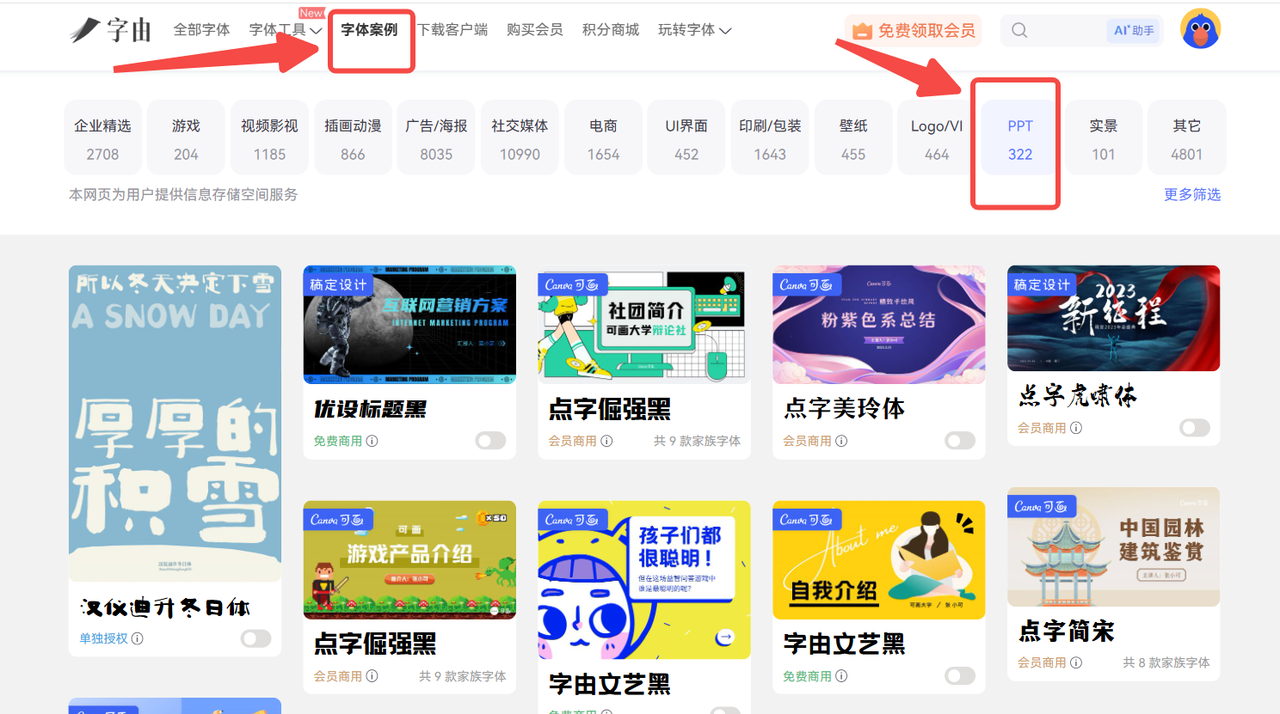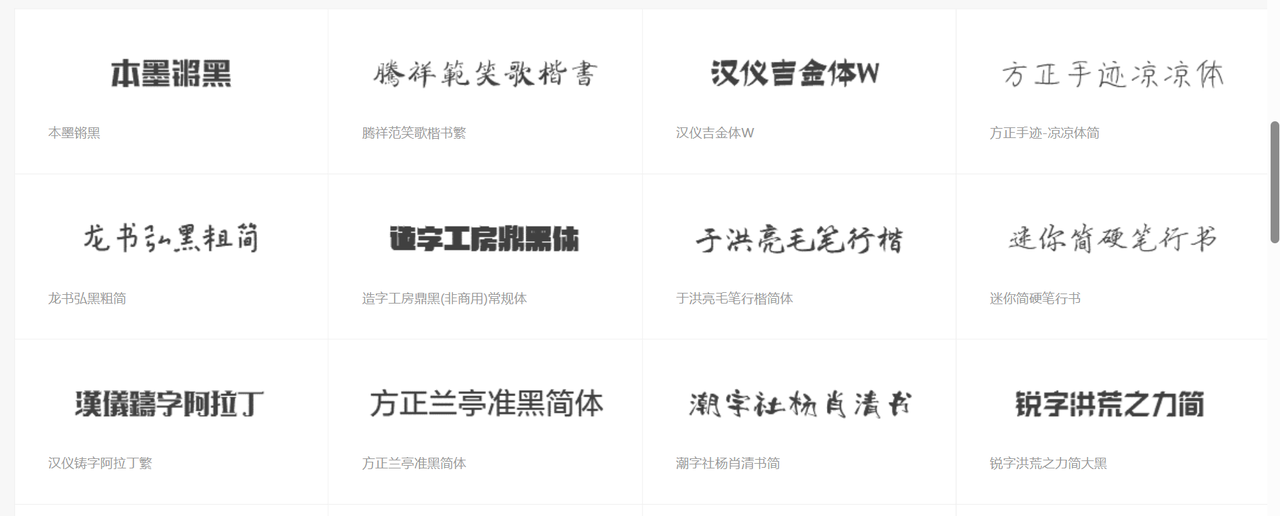
理想的PPT字体是什么样?字体使用避坑指南
理想的 PPT 字体是什么样?抛开宋体和微软雅黑,来寻找可以提升质感的 PPT 字体吧!一般来说,我们可以把 PPT 的文字内容划分为两部分,即标题和正文。像标题,既要凸显主题又要保证不突兀,我们就可以选择黑体或者楷体。而正文由于字数过多,保证排版的同时也不能丢掉可读性,我们就可以看一下无衬线体,比如阿里巴巴普惠黑。而好用的字体也离不开方便使用的字体网站,接下来,本文就将结合几个好用的字体网站来为你推荐更理想的 PPT 字体,一起往下看吧!
1、多款正版 PPT 字体,前往【字由】直接使用
字由是一个素材丰富,风格多样的字体网站,如果你在设计 PPT 时,对于字体的使用没有任何思路的话,那么可以先来【字由】中寻找灵感。字由站内汇集了上万款精品正版字体素材,不仅包含常用的中文字体,还有英文字体,日文,韩文和泰文等,即便是需要做小众语言的 PPT 设计,也能够在字由中找到喜欢的字体。不仅字体素材丰富,字由站内的字体风格也十分多样,不管是需要简约风还是古典风,亦或是卡通风,手写风,科技感,字由站内均有对应的字体素材可供挑选,满足你设计 PPT 时的多种用字需求。
如果面对上万款字体素材,不知该如何下手的话,不要着急,字由还有另一个好用的功能可以帮助你。打开字由官网后,我们可以访问导航栏中的【字体案例】区域,这里按设计场景分类提供了或许更合适你使用的字体素材。我们将设计场景选为 “PPT”,之后在下方就能看到官方推荐的在 PPT 设计中更常用,更好用的字体素材。
以答辩 PPT 为例,我们在规划 PPT 的文字内容时,标题部分传递主题信息,肯定要突出显示,我们就可以选择比较醒目的字体,例如优设标题黑,字由文艺黑,点字简宋,点字倔强黑等,而正文部分由于传达的信息比较多,我们在保证字体美观度的同时也要确保可读性,正文就可以选用非衬线字体,比如 Milky Han Te 家族字体。以上字体都可以在字由中立即使用,并且均拥有正版授权,无需担心侵权风险。
2、优品 PPT:高质量 PPT 网站,精美 PPT 字体推荐
优品 PPT 是一个专业设计 PPT 的网站,它站内提供了周全的 PPT 设计服务,从 PPT 背景到内容图表,再到 PPT 素材,都可以在站内查找。当然,站内也提供了 PPT 字体库,只不过相比于字体网站,它站内的字体素材可选性就十分有限。
优品 PPT 站内的字体主要包含书法字,创意字,黑体,宋体,圆体和楷体,站内的字体分类比较简单粗暴,并没有将字体素材进一步划分。不过这样可能也会将理想的字体素材更快速地筛选到面前,有利有弊。优品 PPT 无需登录也可以使用,不过需要注意的是,站内的字体并不是完全都支持商用的,有部分字体标注了 “非商用” 字样,在使用字体的时候需要多加注意,以免侵权行为的发生。
3、字体视界:提供单款字体授权,放心商用
字体视界也是一个非常有名的字体网站了,如果是专业做设计的朋友,在工作中很有可能用到过这个字体网站。它站内的字体并不是按字体特色来分类,而是按字体用途划分的。所以访问官网后,在查找字体时,我们就能看到网站导航上列出的 “节日用字”,“电商用字”,“印刷用字”,“广告用字” 等等,这个功能和字由的【字体案例】有点相似,本质上都是为了方便用户更快地找到理想的字体。